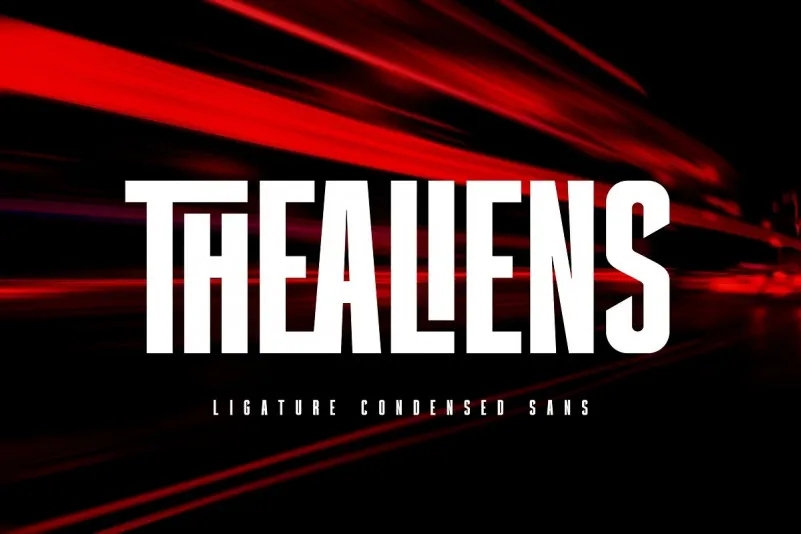
The Aliens Font – Download Grátis
A fonte “The Aliens” é uma tipografia serif que traz à tona uma mistura moderna e ativa, inspirada no título de um adesivo esportivo. Seu design, que inclui a densidadeia e o peso de cada glifo, resulta em uma fonte única com uma ligação que torna-a ainda mais distintiva. A ideia para esta tipografia surgiu da necessidade de criar um tipo de letra com um aspecto vigoroso e moderno, perfeitamente adaptável para qualquer aplicação visual que precise de uma aparência desafiadora e atraente. Será uma excelente escolha para criações gráficas que precisam se destacar, seja ela em cartazes ou em materiais digitais.